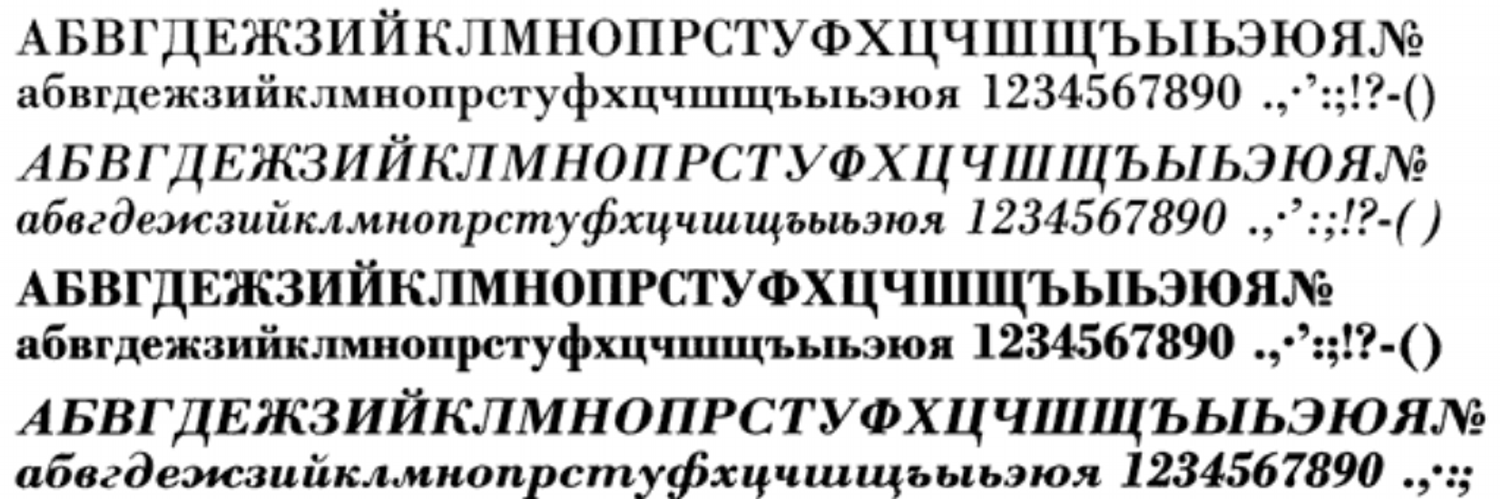
Лучшие бесплатные шрифты для дизайнеров
Шрифт, который используется для отображения текста, влияет на его восприятие. Поэтому в этой статье мы собрали лучшие бесплатные шрифты для веб-дизайнеров 2016 года, которые помогут вашим печатным материалам и сайтам выглядеть профессионально.
10 лучших шрифтов с поддержкой кириллицы
Качественные кириллические шрифты нелегко отыскать, но все же сейчас их гораздо больше, чем раньше. Список ниже содержит как распространенные варианты с засечками и без, так и ультраэлегантные шрифты для особых случаев.
1. Nord — шрифт без засечек, который доступен сразу в 4 вариантах (Light, Medium, Regular и Bold). Характеризуется скругленными краями и интересными выступающими элементами (обратите внимание на букву «Я») и подойдет для заголовков или выделения отдельных элементов:
2. Шрифт Lora доступен в вариантах Regular, Bold, Italic, и BoldItalic, но у него есть засечки и его лучше использовать для основного текста:
4. Lato — еще один шрифт без засечек с просто потрясающим количеством поддерживаемых языков: 100 языков с латинским и 50 языков с кириллическим алфавитом, а также греческий! Доступен в вариантах Regular, Bold, Italic, Light, BoldItalic, LightItalic.
5. Шрифт Sangha создавался на основе индийских мотивов и будет хорошо выглядеть на тематических веб-сайтах, посвященных культуре Востока:
6. Arvo — шрифт типа Terminal, который можно использовать для отображения примеров кода на странице:
7. Frenchpress — шрифт без засечек для особых случаев, например для билетов или пригласительных:
8. Шрифт Proba Pro доступен бесплатно только в вариантах Regular и Italic, но этого достаточно для качественного оформления текста на странице:
9. Intro Condensed — уплотненный вариант известного шрифта Intro, который его создатели рекомендуют использовать для заголовков и плакатов.
10. Шрифт Poiret One выглядит очень элегантно, но в отличие от Frenchpress будет уместен и на веб-страничках:
10 лучших шрифтов с поддержкой латиницы
Если вы работаете с англоязычными заказчиками, то перед вами открываются практически безграничные возможности, ведь именно английские шрифты пользуются особой популярностью. Часто их создатели делают одно или несколько начертаний шрифта бесплатным для личного и коммерческого использования, чтобы привлечь внимание к платной версии шрифта.
1. Volkorn — один из первых шрифтов с засечками, которые стали доступны на Google Fonts. Он поддерживает 8 начертаний:
2. Kaushan Script — аккуратный и читабельный рукописный шрифт, который подойдет как для веба, так и для печатных материалов:
3. Stroke подойдет для иллюстраций или написания слоганов и заголовков. Начертания Regular, Bold и Light распространяются бесплатно:
Шрифт Montserrat без засечек хорошо подойдет для заголовков и посадочных страниц:
5. Oswald — классический чуть сжатый шрифт без засечек, который будет выглядеть хорошо на любых устройствах:
6. Jura — элегантный шрифт со скошенными засечками и круглыми формами, лучше всего подойдет для подзаголовков или основного текста:
7. Exo 2 — универсальный технологичный шрифт с несколькими начертаниями, поэтому его вполне хватит для оформления большинства текстовых элементов на странице:
8. Pompiere подойдет вам, если вы ищите элегантный, но не слишком серьезный шрифт:
9. Aclonica — еще один яркий шрифт для оформления запоминающихся заголовков и печатной рекламной продукции:
10. Museo — шрифт без засечек, который выглядит хорошо при маленьком и большом размере кегля, а значит подойдет как для отображения пунктов меню, так и для основного текста страницы. Доступен бесплатно в вариантах Museo Sans 500 и Museo Sans:
В этой статьи мы привели шрифты для профессиональных графических дизайнеров, которые можно использовать для дизайна страниц или печатных материалов.
- Не используйте слишком контрастные шрифты — может получиться так, что каждый из них будет перетягивать внимание на себя, отвлекая читателя от содержания.
- Но и не выбирайте слишком похожие — они будут сливаться, и создавать ощущение незаконченности.
- Создавайте визуальную иерархию — вспомните, как обычно выглядят печатные газеты: в них четко просматривается структура заголовков.
- Не забывайте о контексте — ведь дизайн создается не просто так, а в соответствии с потребностями конкретной компании.
- Не используйте больше трех разных шрифтов на одной странице.